Tuyển chọn bộ font chữ tiếng Việt đẹp và bắt mắt nhất dành cho máy tính Windows 10
Windows 10 hỗ trợ rất nhiều font chữ tiếng Việt đa dạng. Tuy nhiên, không phải font nào cũng đẹp, dễ đọc và phù hợp để sử dụng trong mọi tình huống. Vì vậy, FPT Shop sẽ tổng hợp một danh sách gồm các font chữ tiếng Việt đẹp và bắt mắt nhất trong bài viết này. Ngoài ra, bạn cũng sẽ được học cách tải về và cài đặt những font chữ này.
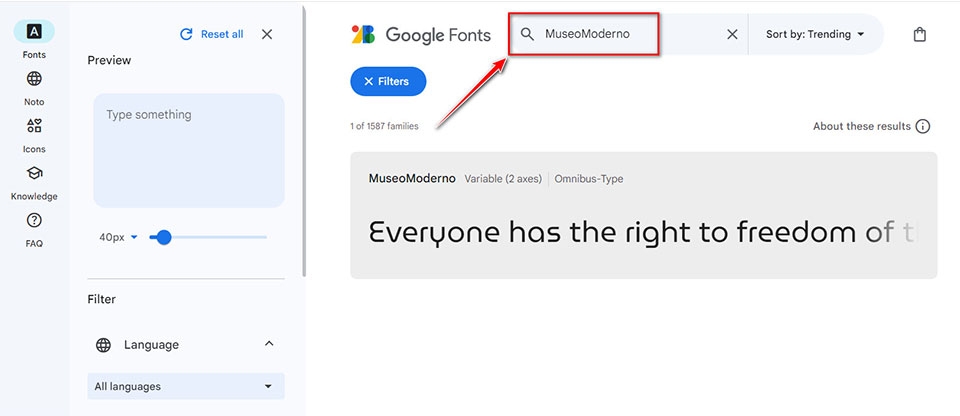
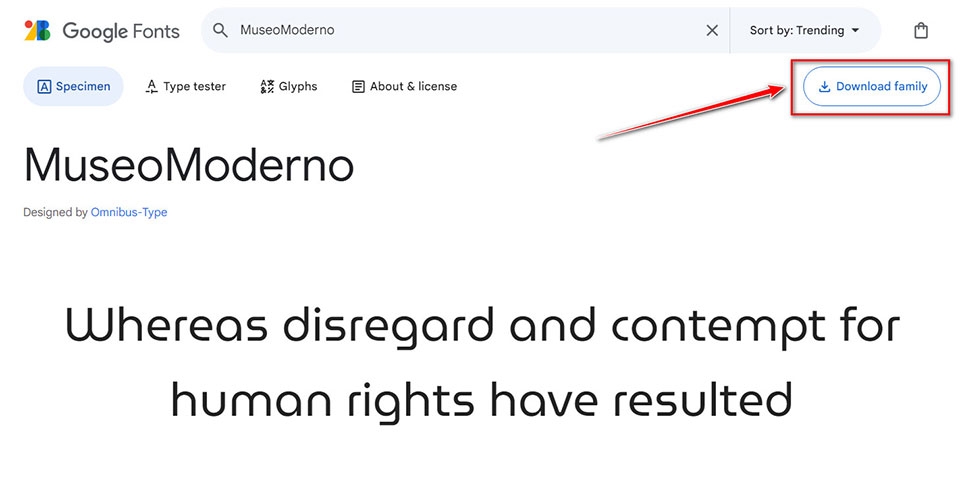
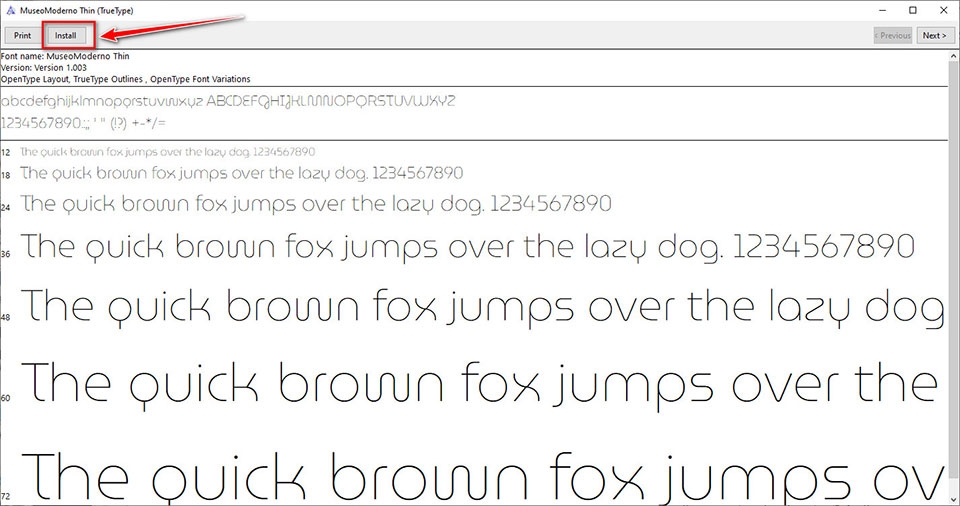
Các bộ font chữ tiếng Việt đẹp và bắt mắt nhất
Sau khi bạn đã học được cách tải về và cài đặt font chữ tiếng Việt trên Windows 10, FPT Shop sẽ giới thiệu đến bạn một vài font chữ tiếng Việt đẹp và bắt mắt nhất hiện nay.
MuseoModerno
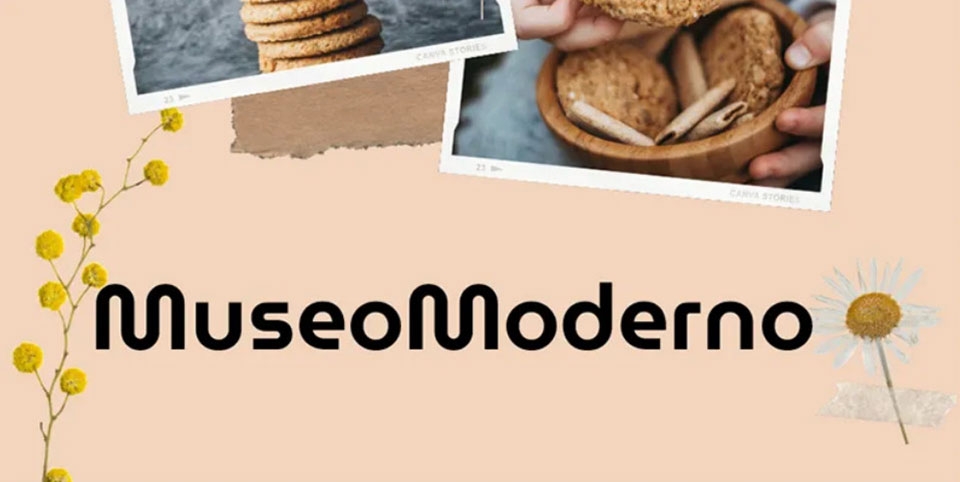
MuseoModerno là một font chữ độc đáo, mang đậm phong cách hiện đại và tinh tế. Được thiết kế bởi Pablo Cosgaya, Héctor Gatti và Marcela Romero, font này lấy cảm hứng từ nghệ thuật châu Âu đầu thế kỷ 20 và phong trào nghệ thuật avant-garde. Điểm nổi bật của MuseoModerno là sự kết hợp hài hòa giữa hình dạng hình học và đường nét mềm mại, tạo nên một vẻ đẹp cân đối, lịch lãm.
Pacifico
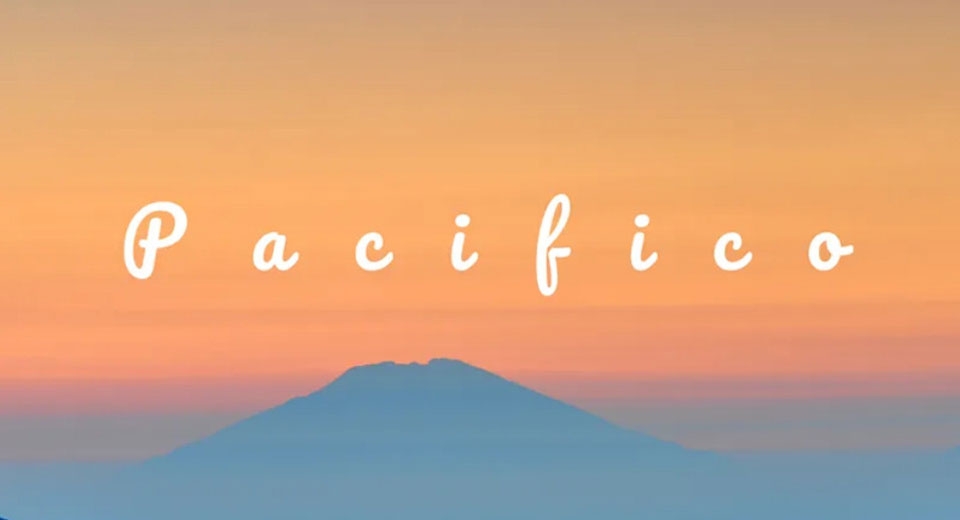
Pacifico là font chữ viết tay mang phong cách brush script. Nó được thiết kế bởi Vernon Adams và lấy cảm hứng từ văn hóa lướt sóng Mỹ của những năm 1950, mang đến một cảm giác tươi vui và tự do. Pacifico nổi bật với các nét chữ mềm mại, uốn lượn, tạo cảm giác thư giãn và thoải mái. Font Pacifico phù hợp cho các thiết kế mang tính cá nhân, như lời chúc, thiệp mời hoặc các dự án sáng tạo khác cần một chút phong cách retro và lãng mạn.
Roboto
Roboto là một font chữ sans-serif neo-grotesque. Nó được phát triển bởi Google và là font chữ hệ thống cho hệ điều hành Android. Thiết kế của Roboto mang đặc trưng là sự kết hợp giữa cấu trúc cơ khí và hình dạng hình học, nhưng vẫn giữ được sự thân thiện và mở cửa thông qua các đường cong mềm mại. Font này phù hợp cho cả in ấn và hiển thị trên màn hình.
Dancing Script
Dancing Script là một font chữ script đầy sức sống với các chữ cái nhảy múa và thay đổi kích thước một cách nhẹ nhàng. Được thiết kế bởi Pablo Impallari, font chữ này mang đến một phong cách viết tay tự nhiên và lôi cuốn. Dancing Script cũng đã được Việt hóa, giúp người dùng Việt Nam có thể sử dụng một cách thuận tiện trong các dự án tiếng Việt của mình.
Noto Serif
Noto Serif là một phần của dự án Noto của Google với mục đích tạo ra một loạt font chữ hỗ trợ tất cả ngôn ngữ trên thế giới. Nó có thiết kế cổ điển với các đường nét mềm mại và cân đối, mang lại vẻ đẹp truyền thống nhưng vẫn hiện đại. Bộ font này phù hợp cho cả văn bản in và hiển thị trên màn hình, từ sách và tạp chí đến trang web và ứng dụng di động.